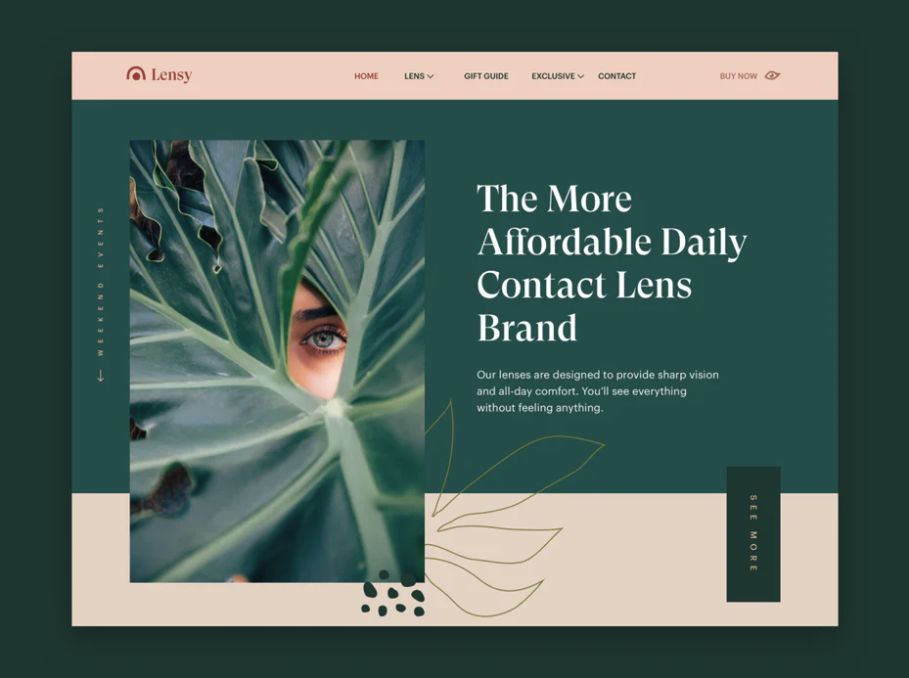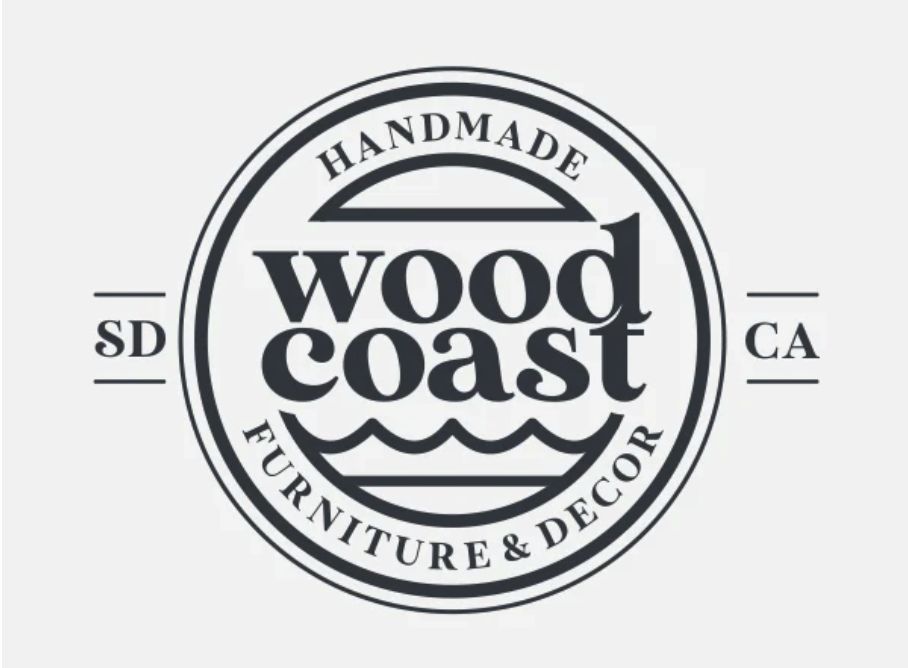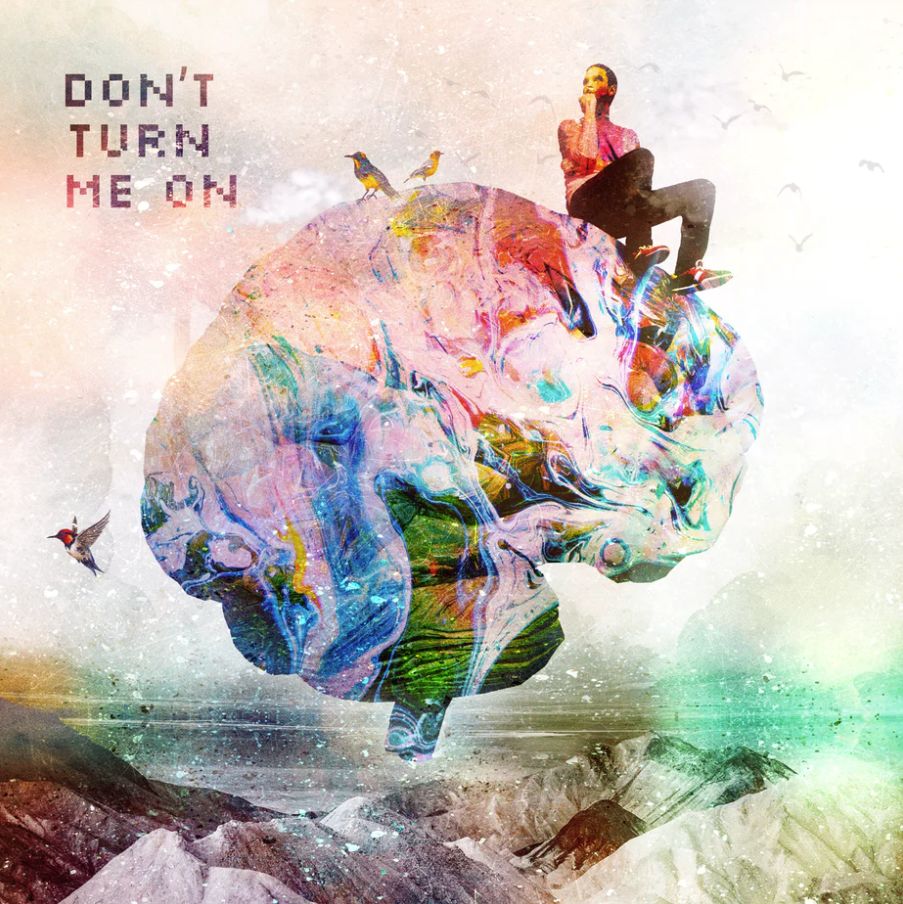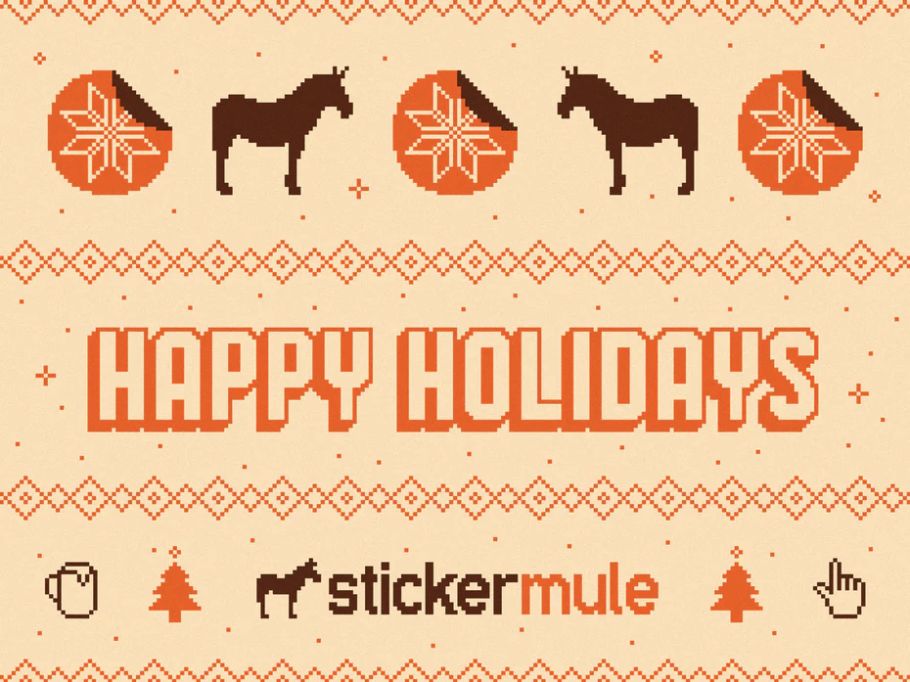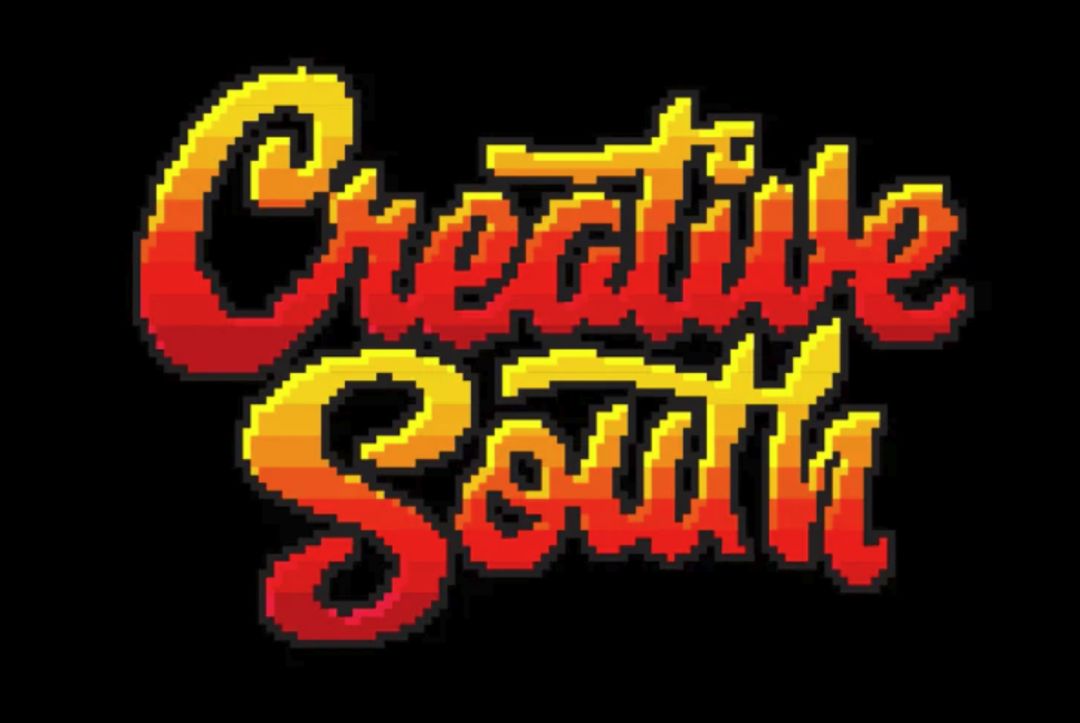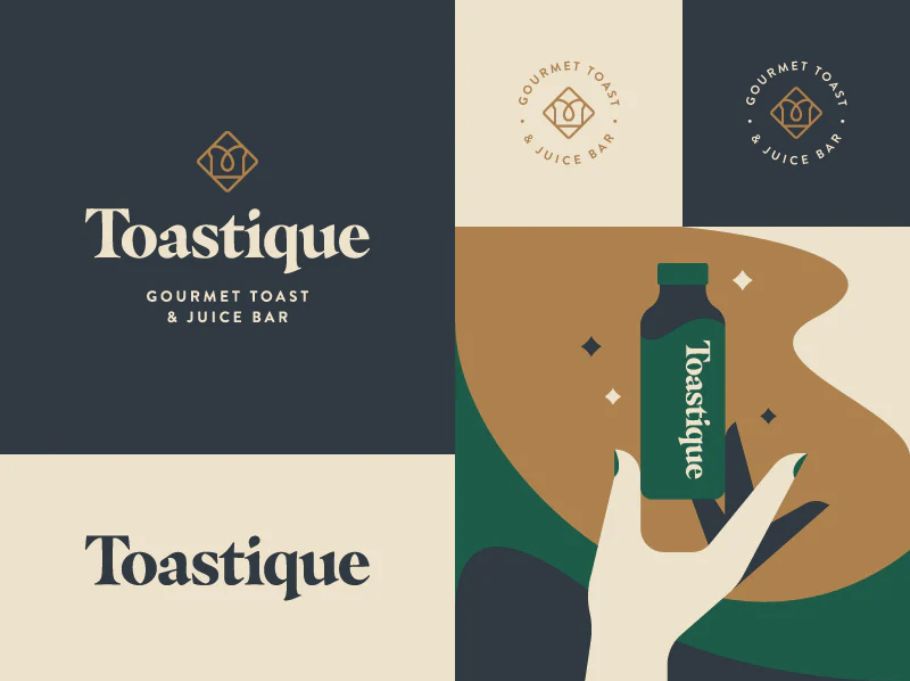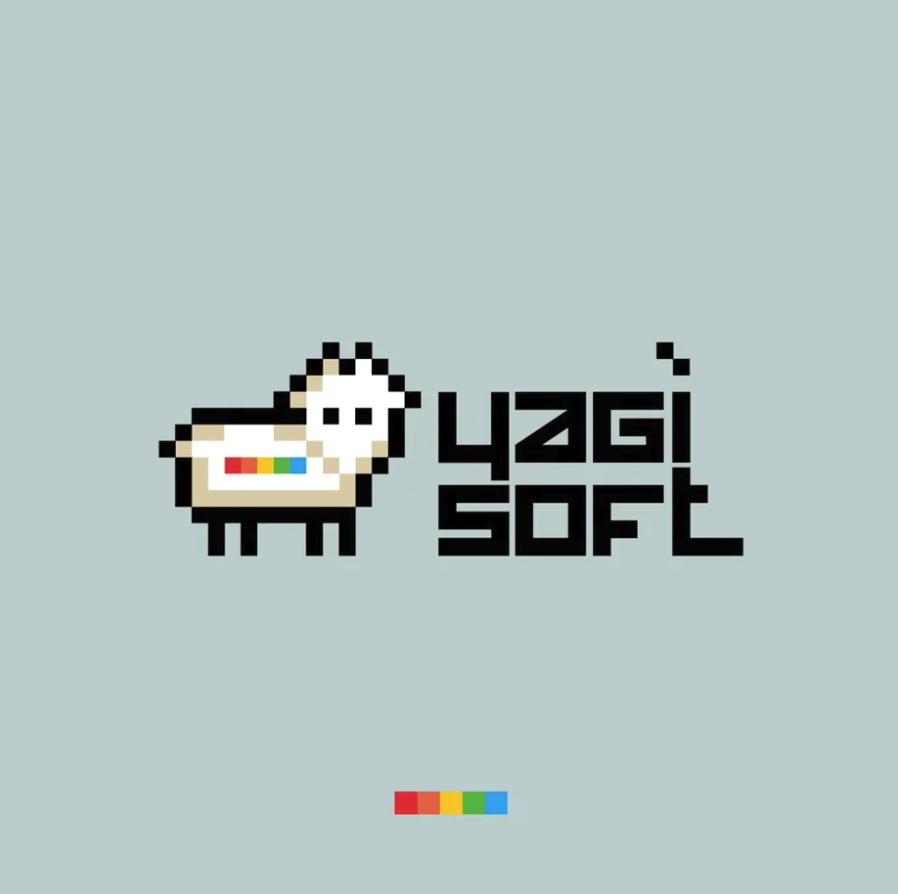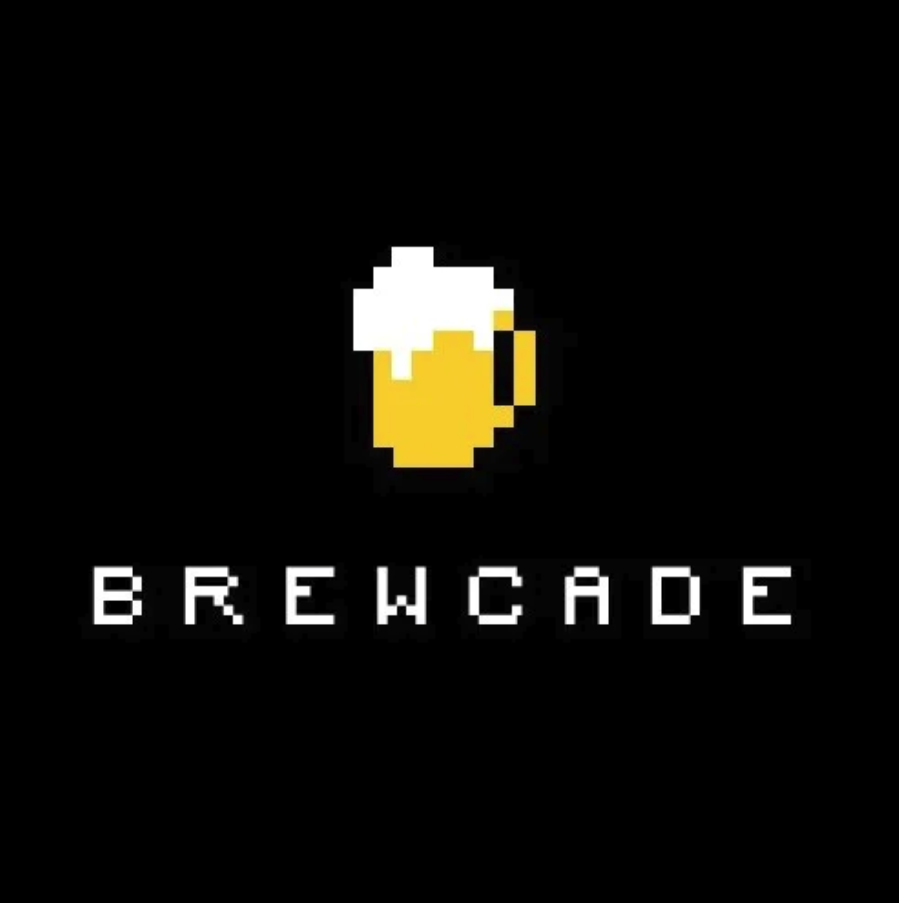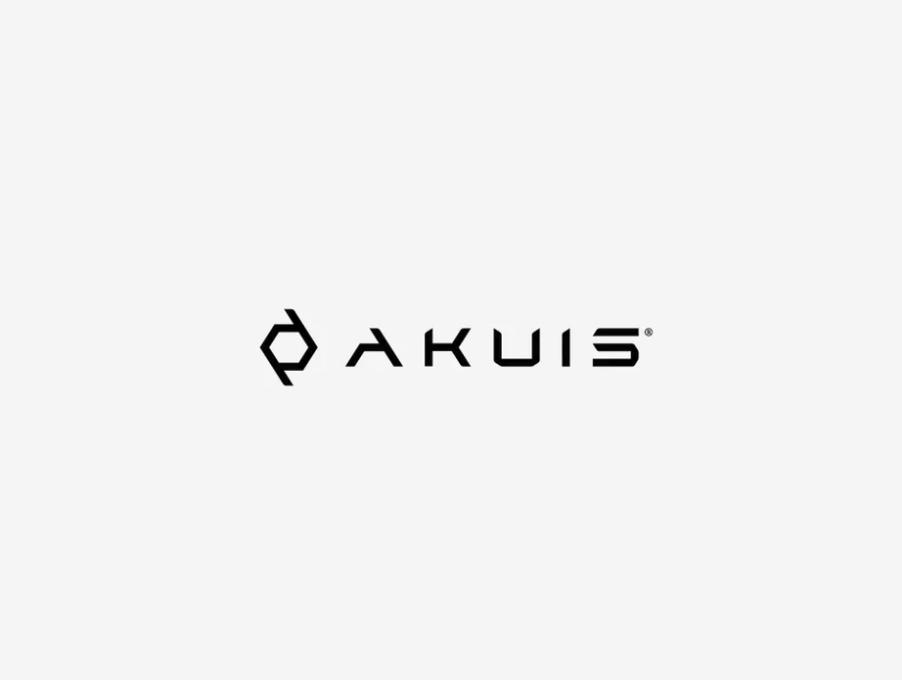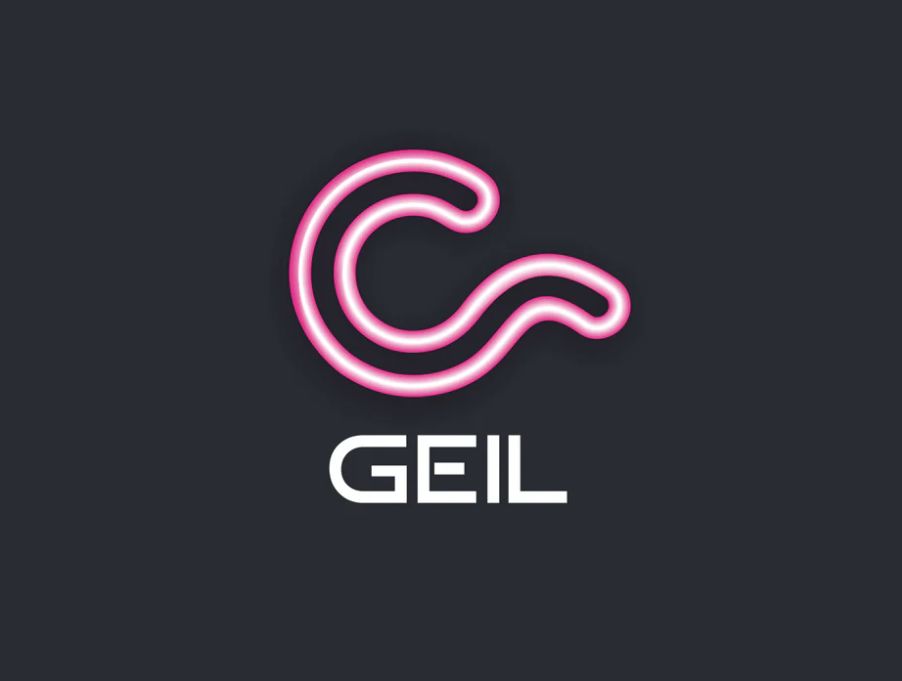
眼看着还有半个月,就要迈入2020的大门,新一年的字体创意都有了吗?今天柚子就给你超前点播!
赛博朋克
2020年的配色方案将更加充满活力,这其中离不开赛博朋克,它能为观者创造了一种超现实体验,照亮我们的世界。
街头艺术
涂鸦和街头艺术具有复古的吸引力,能让人联想起70年代朋克场景,2020年,这一趋势将卷土重来。
手绘字体
随着极简主义的发展,消费者将渴望手工制作的设计,而设计师也必须提供能够与他们交流的字体,建立更多个性化的联系。
强烈阴影
通过用硬线创建字体的3D形式,巧妙地模仿了现实生活中的对象(例如凸起的纽扣,雕刻的硬币或斜面的石头),虽然看起来是一个平面图像,但非常逼真,有触摸感。
人性化衬线
我们经常倾向于使用无衬线字体,因为它们一直被认为更“现代”。但是,我们看到品牌的徽标和网站中使用大胆,高对比度衬线的字体明显增多,因为它们更适合讲故事……
像素字体
像素艺术从70年代发展到90年代,如今在2020年,又再次崭露头角。对于几代喜欢视频游戏的人来说,这些字体既有趣又异想天开。
极简主义
许多字体设计师正在尝试去除字母的部分笔画,使用负空间,以创建更宽的形状,让人感受到无限可能。
霓虹风格
最后一个很熟悉了,无论它们是亮的还是深的,轮廓都是创造发光效果,引人注目。